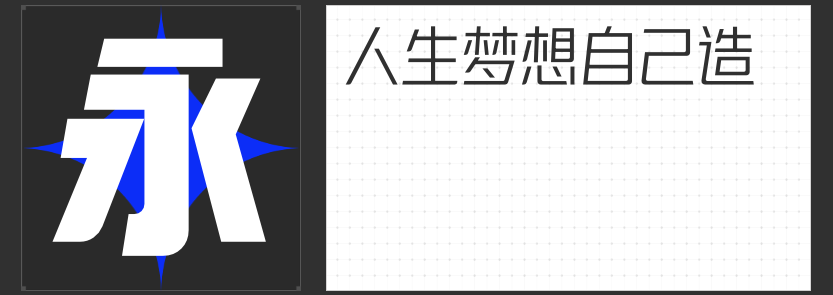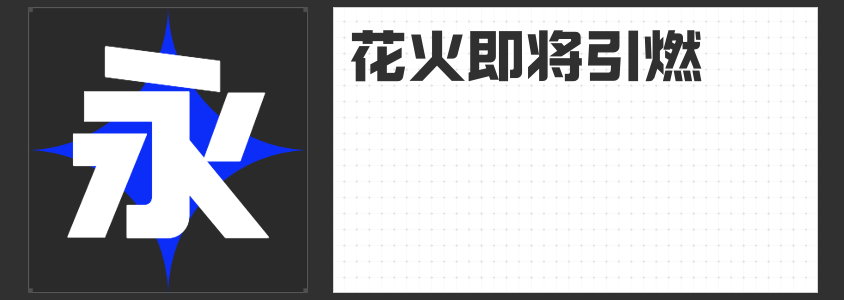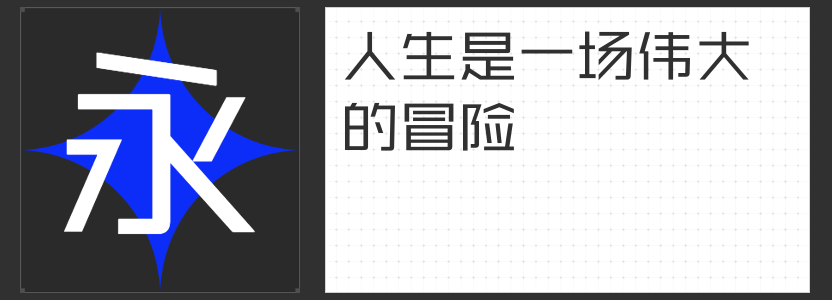
三款高效能可变字体推荐:为设计注入灵活基因
在数字化设计场景中,可变字体以动态适配、多维度调节的特性成为创意表达的利器。本文推荐三款来自励字工坊的优质可变字体,它们以独特的风格语言与实用性能,为标题、品牌视觉及多场景设计提供精准解决方案。
1. 励字勇敢黑简 可变字体
作为无衬线家族的代表,励字勇敢黑简以粗壮笔划与几何化结构传递强烈视觉冲击。其笔触末端采用钝角处理,避免尖锐感的同时提升阅读舒适度,横竖笔画的均衡粗细确保远距离辨识度。设计师可通过字重轴调节从纤细到浑厚的梯度变化,轻松驾驭杂志封面、活动主视觉等需要强势吸睛的场景,尤其在金属质感或高对比度配色方案中表现卓越。
2. 励字可变志向黑简
这款字体突破传统黑体的方正框架,在转折处植入微弧圆角,形成刚柔并济的独特气质。字面框经过精密计算,保证小字号下的清晰度,同时圆润细节缓解黑体易产生的压抑感。其可变特性支持字宽与字高的独立调节,适配移动端横竖屏切换、响应式网页等动态布局需求,在科技品牌LOGO或APP导航栏中展现出专业性与亲和力并存的视觉魅力。
3. 励字造梦简 可变字体
以极致简洁为核心理念的励字造梦简,通过方头方尾的笔形切割与2:1的横竖粗细对比,构建出极具现代感的视觉节奏。该字体在保留无衬线字体高效传播属性的基础上,通过可变轴实现从纤薄到厚重的多维切换,既能化身极简海报的视觉焦点,也可作为正文排版的基础字款。其高包容性使其广泛适用于包装设计、数据可视化图表及商业空间导视系统。
三款字体虽风格迥异,却共同践行“形式追随功能”的设计哲学。这三款字体风格各有不同,为设计师提供覆盖品牌调性、媒介特性与用户体验的完整解决方案。